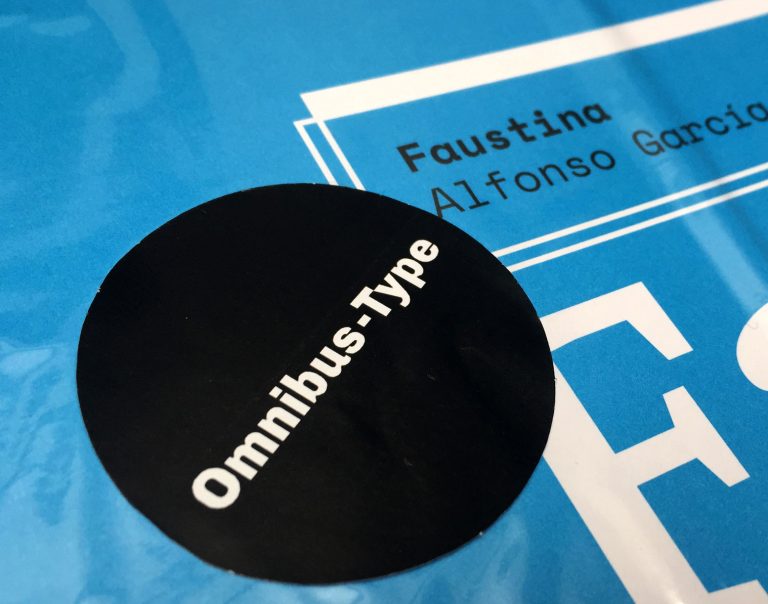
No hace tanto que hablábamos de la enorme libertad creativa de los diseñadores de tipografía latinoamericanos, al igual que de la sólida oferta de estudios universitarios de alto nivel como la Maestría de Tipografía de Buenos Aires a partir de la cual se ha creado «una cantera de la disciplina que ha transformado el continente en un paisaje apasionante para cualquier amante de las letras bien hechas».
Uno de los profesores de tipografía de la Universidad de Buenos Aires, responsable en gran medida de la renovación y el impulso tipográfico en Lationamérica, es Pablo Cosgaya. Este veterano profesor no solo afirma su compromiso con la tipografía desde su puesto de docente académico, sino, además, desde su fundición tipográfica digital, Omnibus Type, una gran empresa que cuenta con un equipo talentoso de diseñadores de tipos, unidos por la misma pasión por las letras. Como dicen ellos mismos, «para nosotros las tipografías nacen, crecen y se desarrollan como seres vivos con pensamientos latentes, conocimiento y emociones».
Omnibus Type es una de nuestras fundiciones tipográficas digitales favoritas por ser innovadora en el mercado tipográfico al publicar tipografías profesionales de enorme calidad con licencia de libre uso.
Tipografías marca Omnibus
En esta fundición vas a encontrar un amplio catálogo de familias, unas veinte, de una gran solvencia estética y técnica, y la certeza de que existe una continua evolución y adaptación de sus fuentes a nuevos usos, nuevos lenguajes y nuevas tecnologías. Y volvemos a repetir, todas ellas, bajo licencia de libre uso. Marca de la casa.
Además ofrecen la creación de tipografías a medida, proporcionando una contribución de incalculable valor en la creación o renovación de una identidad visual.
Press Series
Hace poco, la fundición anunció el lanzamiento de Press Series, una magnífica colección de tipografías para publicaciones impresas y digitales, compuesta por un total de 68 tipografías en formatos digitales, listas para impresión, pantalla y sitios web. Todas ellas con licencia de uso libre.
Press Series, está compuesta por 5 familias diseñadas específicamente para el uso en publicaciones periódicas impresas aunque ofrecen, además, la posibilidad de usarse en sitios web y aplicaciones. Veamos una por una las bondades de estas fabulosas familias tipográficas.
Faustina
Faustina, diseñada por Alfonso García y producida por el equipo de Omnibus-Type, está compuesta por ocho pesos. Su diseño evoca las publicaciones periodísticas de Domingo Faustino Sarmiento (1811-1888), político y escritor argentino, muy reconocido tanto por su labor en favor de la educación pública como por su contribución al progreso científico y cultural de Argentina.
Una tipografía con una altura x amplia, ideal para texto pequeños y compactos y que permite resolver todo tipo de jerarquías en diseño editorial.
Manuale
Manuale, diseñada por Pablo Cosgaya y Eduardo Tunni, fue producida por el equipo de Omnibus-Type. Compuesta por ocho pesos, su diseño se inspira en los primeros impresos en territorio argentino.
Una tipo que destaca por sus itálicas con características de cursivas, unas contraformas amplias, serifs afilados y un completo set de glifos para idiomas latinos.
Archivo
Archivo es una neogrotesca compuesta por ocho pesos. Diseñada por Héctor Gatti y producida por el equipo de Omnibus-Type. Esta nueva familia se suma a las Archivo Narrow, Archivo Black y Pragati Narrow, ya publicadas.
Es un nuevo lanzamientos que amplía la gama de uno de los proyectos más populares de Omnibus Type, Archivo Narrow, con más de 25.136.794.139 de visualizaciones en Google Fonts.
Asap Condensed
Diseñada por Pablo Cosgaya y Nicolás Silva, y producida por el equipo de Omnibus-Type. Al igual que Archivo, Asap Condensed viene a ampliar las familias Asap, Asap Symbol y Jaldi (la versión devanagari de Asap). Estas familias destacan por sus terminaciones redondeadas y un mismo ancho para todas las variables. Está compuesta por ocho pesos: regular, medium, semibold y bold con sus correspondientes itálicas.
Saira
Una superfamilia compuesta por 36 tipografías, cuatro subfamilias de ancho, cada una con nueve variables de peso.